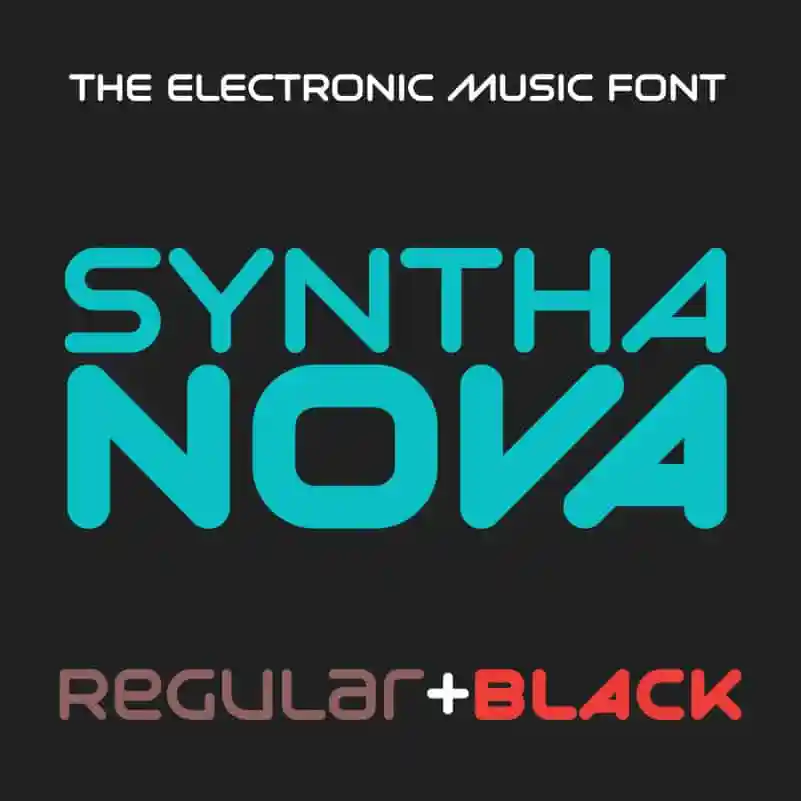
Syntha Nova Display Font – Fonte Grátis
Syntha Nova Display Font
Bem-vindo à descoberta! Introduzimos a Syntha Nova Font, uma fonte para displays com um estilo elegante, feminino e clássico. Ideal para cartas de noiva, marcas e outros produtos criativos. A sua forma única torna-a perfeita para adicionar personalidade ao seu design, seja em rótulos de embalagens, logotipos ou elementos gráficos de marca. Esta fonte é a escolha certa para quem busca uma combinação de elegância e modernidade. Combinar esta fonte com outras letras sem serif pode criar um contraste visual interessante que destaca o design de seus projetos. Seja você designer gráfico, profissional ou criativo em geral, Syntha Nova é a escolha perfeita para levar suas ideias para longe. A sua versatilidade permite que você utilize esta fonte não só nas suas criações digitais, mas também em impressões físicas, tornando-a um ativo imprescindível no seu kit de ferramentas gráficas.